Kursiv
»Kursiv« ist ein paläografischer und typografischer Terminus für eine nach rechts geneigte Schriftstilvariante, eine nach rechts geneigte Schriftlage sowie ein Klassifikationsmerkmal einer Druckschrift oder eines Screen Fonts. In anderen europäischen Sprachen wird sie als »italic«, »italique«, »cursiva« oder »corsivo« bezeichnet.
Semantisch ist der Begriff von der lateinischen Kursivschrift »Cursiva« abgeleitet, einer römischen Verkehrsschrift, die mit einem Griffel auf Wachstafeln oder mit einer sehr schmalen Rohrfeder auf Papyrus geschrieben wurde.
1495 wurden die ersten kursiven griechischen Drucktypen vom italienischen Typografen Aldus Manutius d.Ä. (1449–1515) und seinem bologneser Schriftgießer und Stempelschneider Francesco Griffo (Francesco da Bologna, 1450–1518) nach Vorlagen skriptografischer Verkehrsschriften für den Druck adaptiert.
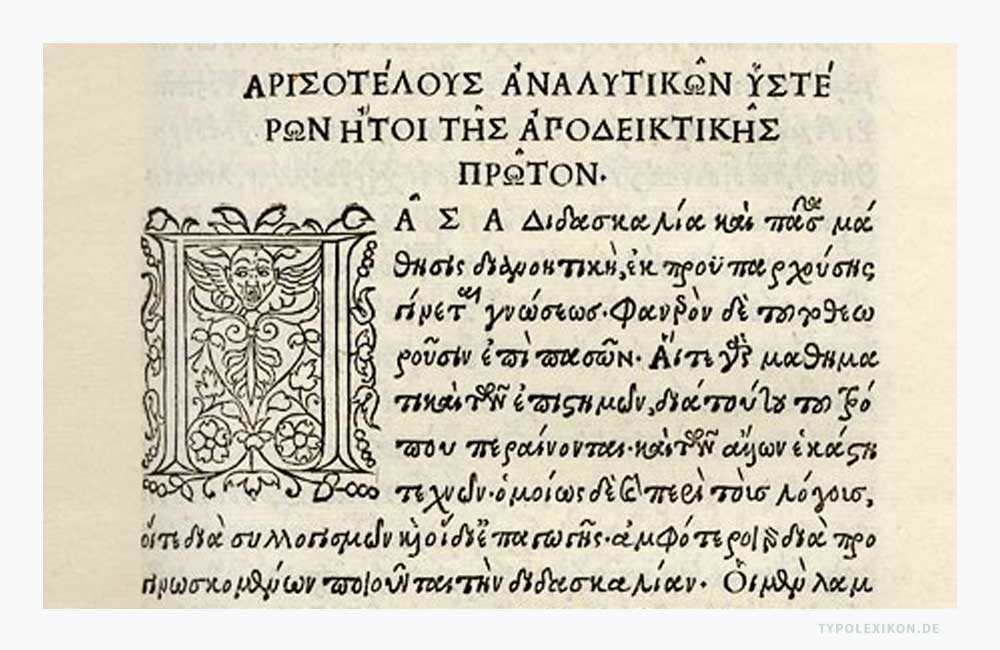
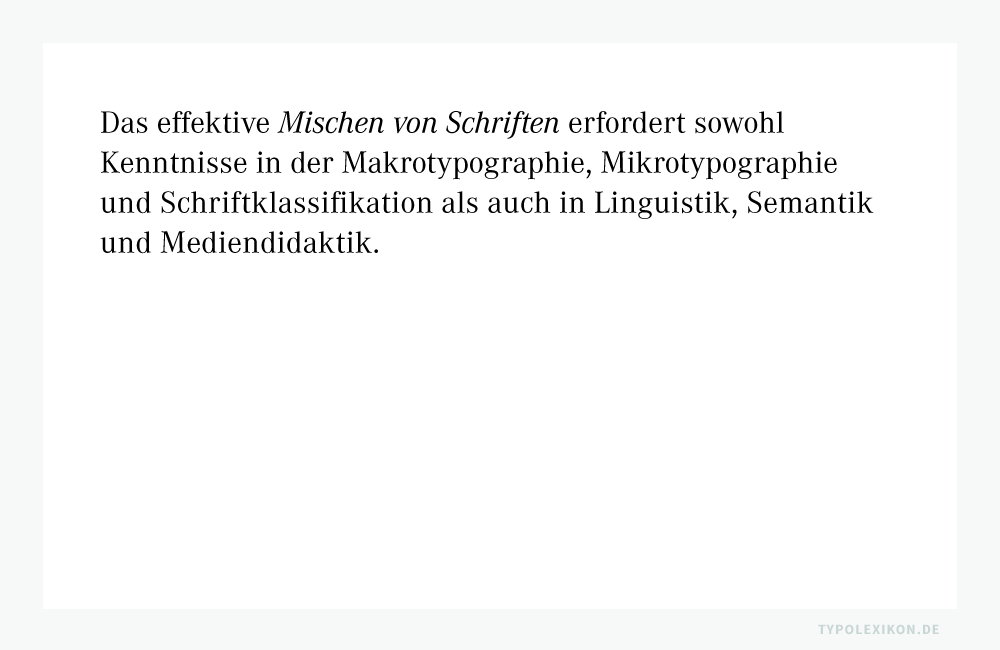
Der kursive Schriftstil gehört zu den Auszeichnungsschriften einer Schriftfamilie und wird primär für leise Auszeichnungen verwendet. Der kursive Schnitt wird in der Schriftmischung als leise Auszeichnung erster Hierarchie, der Kapitälchenschnitt als leise Auszeichnung zweiter Hierarchie bezeichnet.
Bei kursiven Schriftschnitten handelt es sich grundsätzlich um eigenständig gestaltete Schriftstilvarianten. Computergenerierte Varianten, also rechnerisch erzeugte Versionen, gelten in der Typografie als minderwertig, da sie von der Typometrie des originalen Kursivschnitts erheblich abweichen und in der Regel schlechter lesbar sind.
Schriftfamilien und Schriftsippen können über unterschiedliche kursive Schriftstilvarianten verfügen, die in verschiedenen Schriftbreiten, Schriftlagen und Strichstärken existieren, beispielsweise:
- Buch kursiv
- Kapitälchen kursiv
- Kapitälchen kursiv fett
- Kapitälchen kursiv halbfett
- kursiv fett
- kursiv halbfett
- kursiv extra
- kursiv mager
- kursiv schmal
- kursiv schmalhalbfett
- kursiv ultra leicht
- schräg fett
- schräg halbfett
- schräg normal
Unter »kursiv halbfett« versteht man eine Schrift mit normaler Schriftbreite, halbfetter Strichstärke und kursiver Schriftlage. Unter »Buch kursiv« versteht man eine Schriftstilvariante, die insbesondere für das Lesen längerer kursiver Texte optimiert wurde.
Längere Textpassagen in einem kursiven Schriftstil sind im Vergleich zum normalen Schriftschnitt schwerer bzw. langsamer lesbar. Diese Erkenntnis aus der Leseforschung kann jedoch als dramaturgisches Stilmittel (gezielt verlangsamtes Lesen einer Textpassage) in die Gestaltung eines Schriftsatzes einfließen (siehe Schriftmischung).
Kursive Schriftstilvarianten aus den Hauptschriftgruppen Grotesk (Sans Serif) und Egyptienne (Slab Serif) sind erfahrungsgemäß schlechter lesbar als solche aus der Hauptschriftgruppe Antiqua (Serif).